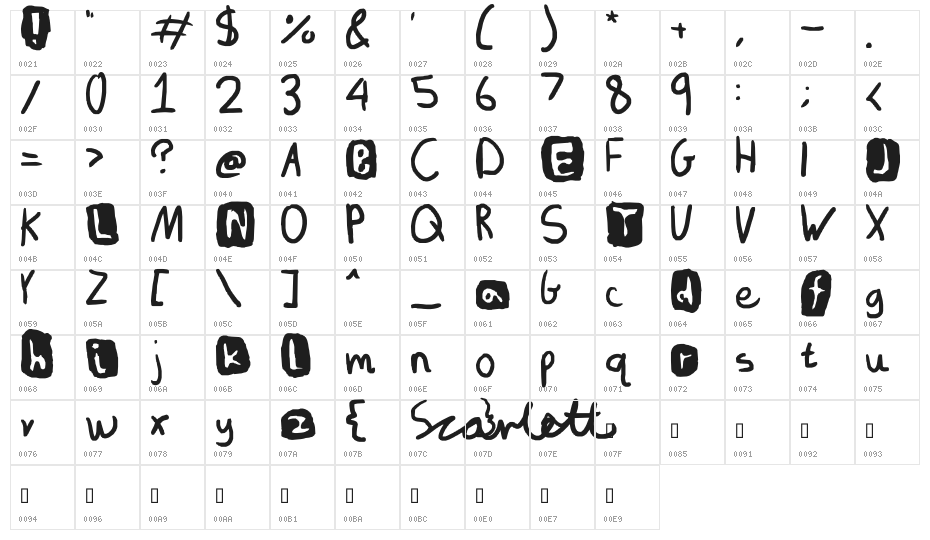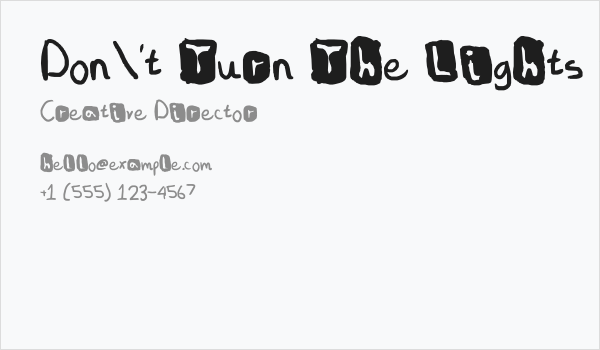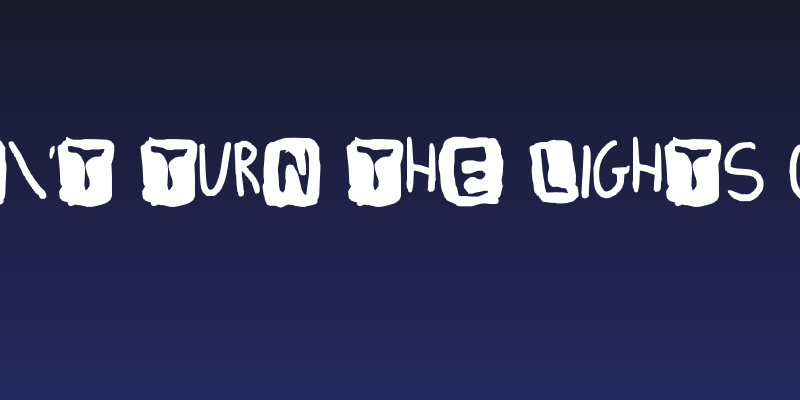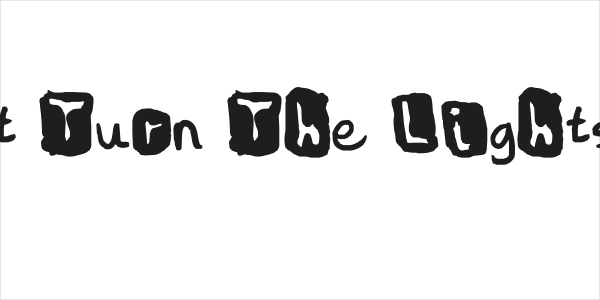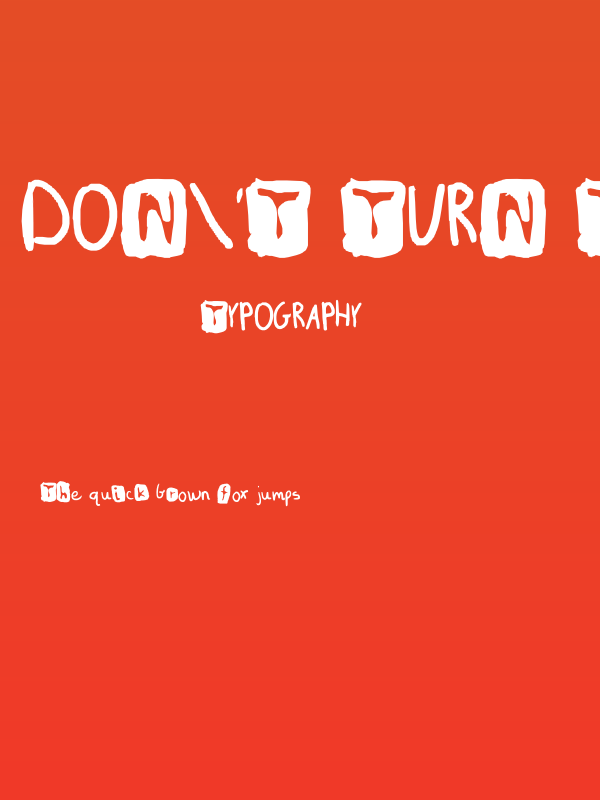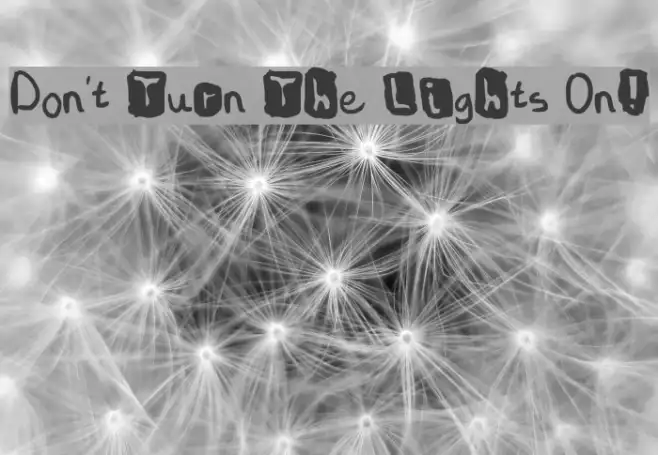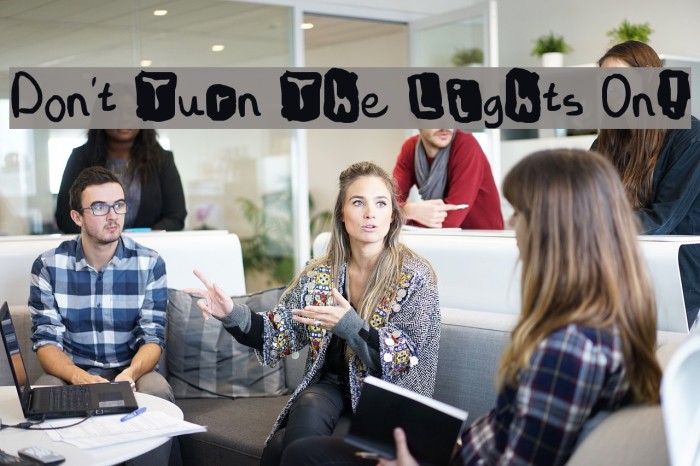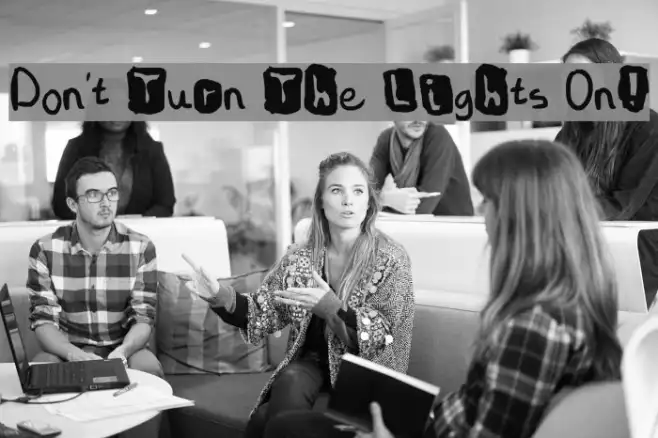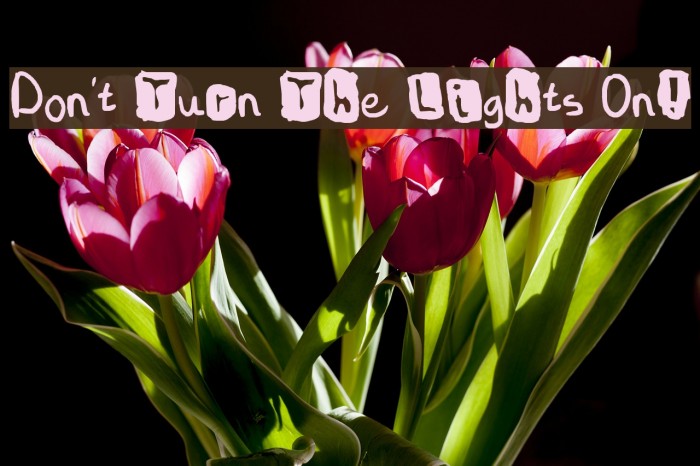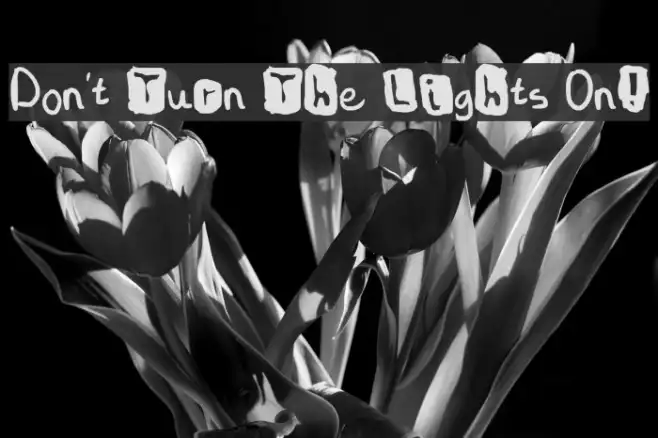
Don't Turn The Lights On! Font
| Stile generale | Playful, Artistic |
| Caso d'uso | Headlines, Posters, Creative Projects |
| Progetti proposti | Ideal for children's books, creative posters, informal invitations, and artistic branding projects. |